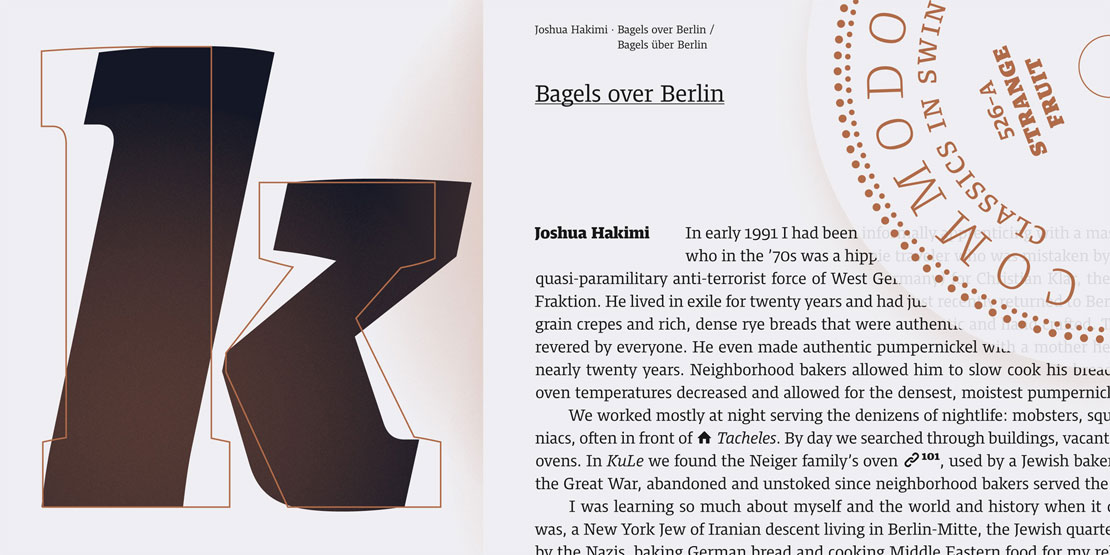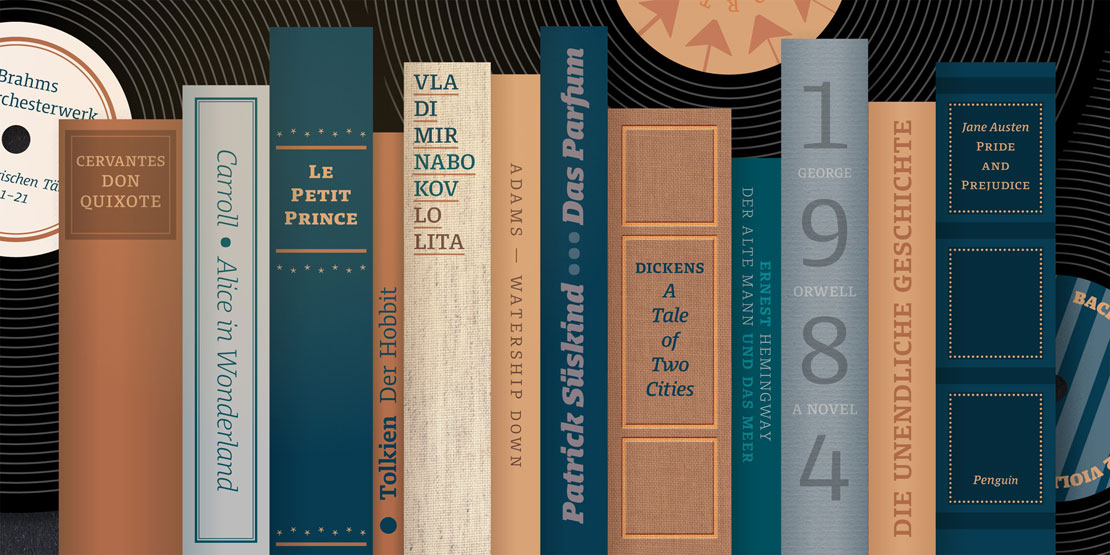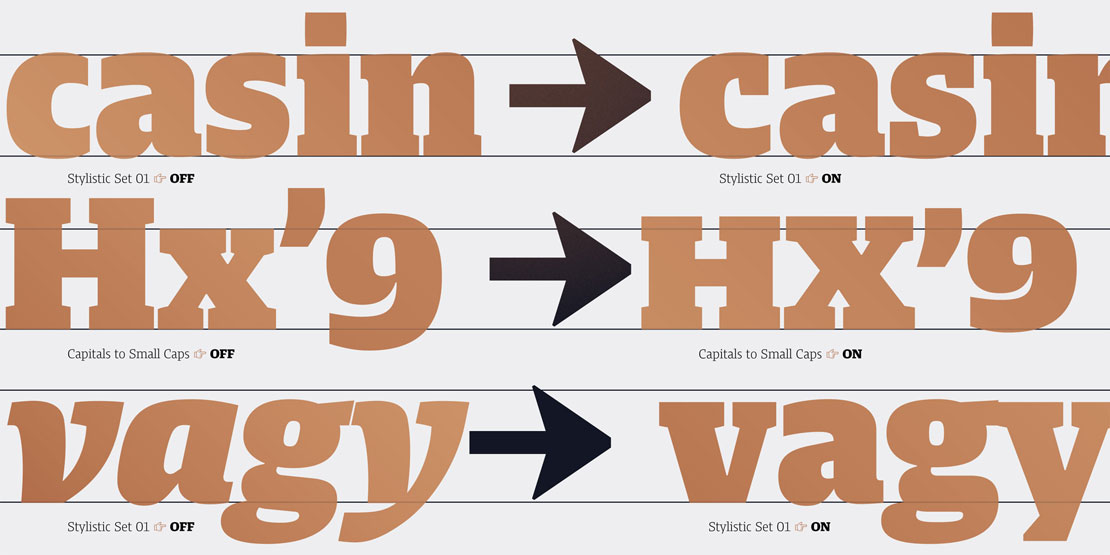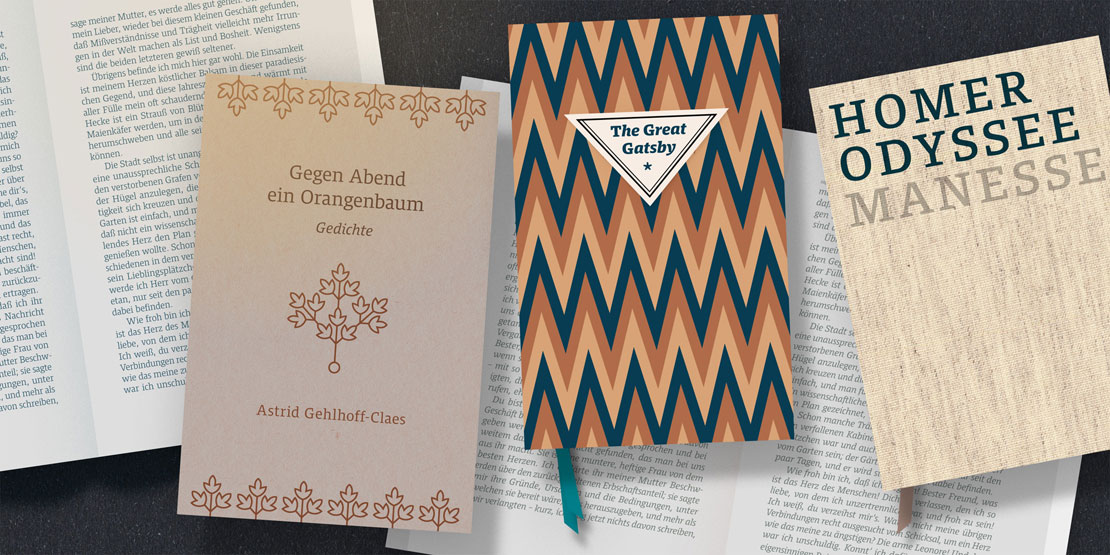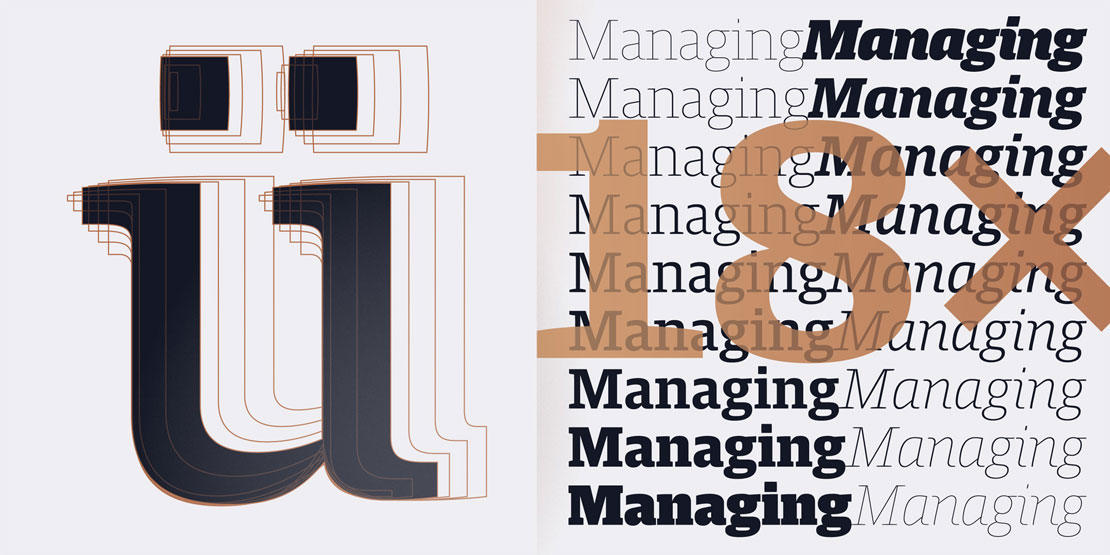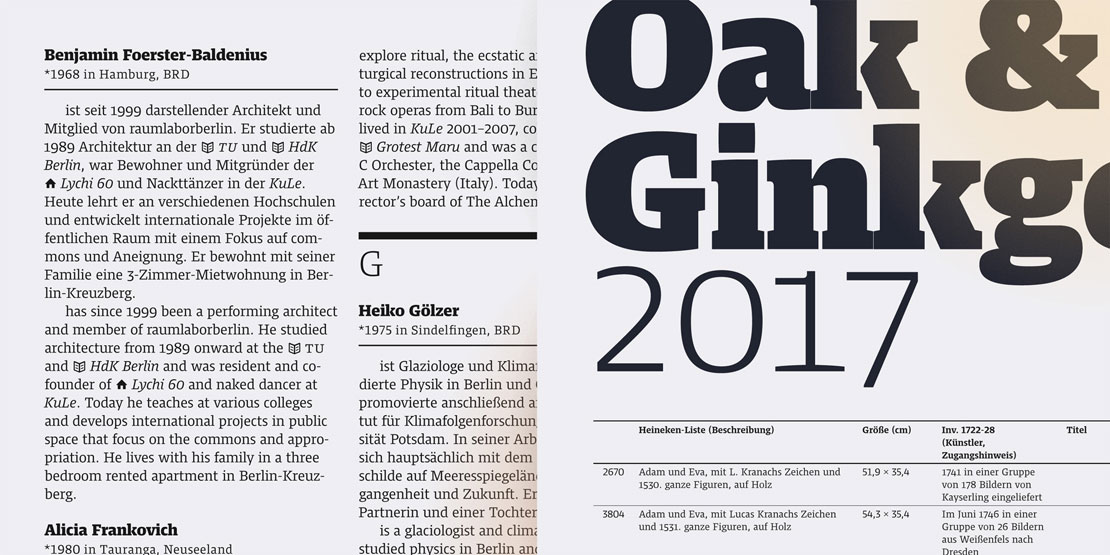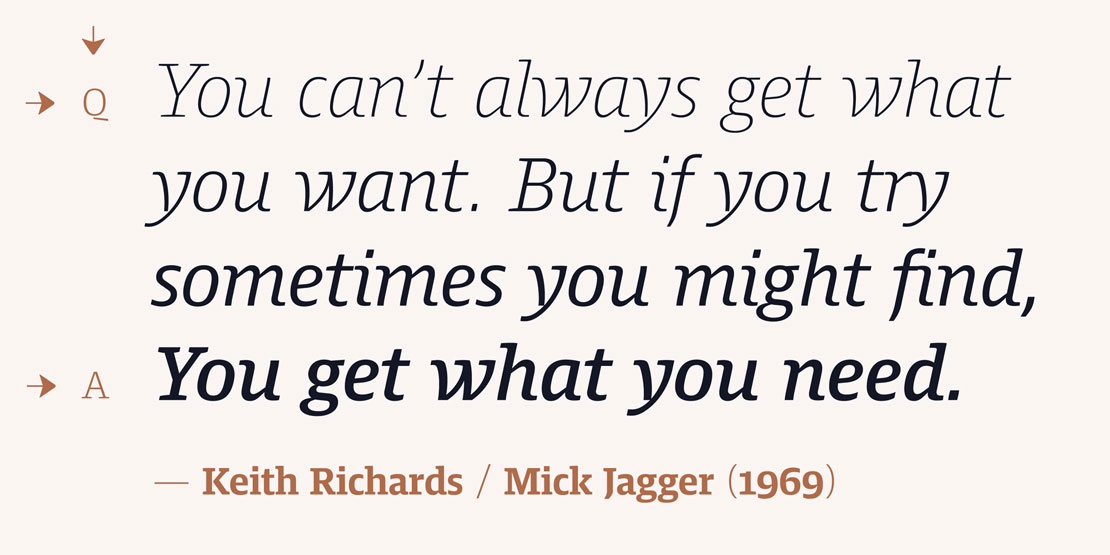
»Harrison Serif Pro« von den TypeMates
Die TypeMates aus Hamburg haben eine neue Schrift veröffentlicht. »Harrison Serif Pro« ist eine zeitgemäße Slab Serif im Spannungsfeld von kompetent bis leger.
Die Harrison Serif Pro von Jakob Runge und Lisa Fischbach ist eine robuste Slab Serif mit dezentem Strichstärkenkontrast, die Rationalität mit einem freundlichen Ton kombinieren soll. Die leicht gebogenen und teils stark betonten Serifen zeigen die sanfte Seite der Harrison Serif die im Kontrast zur gradlinigen Struktur der fast schon eckigen Innenformen, den offenen Punzen und der starken Betonung der Horizontalen steht.
Harrison wurde für längeren Text am Bildschirm und für UI Anwendungen gestaltet. Die ausgearbeiteten Details der Schrift sollen laut den Kreativen vor allem in hochauflösenden Medien und im gedruckten Umfeld zur Geltung kommen.
Harrison Serif bietet ein breites Spektrum an Gewichten – von hauchfeiner Haarlinie bis zur dunkelschwarzen Ultra sowie kursive Schnitte. Durch einen Mix aus echter Kursiven und schlicht geneigtem Winkel verbinden sie handschriftlich-verspielte, expressive Formen mit der Nüchternheit einer Oblique.
Die Schrift deckt einen breiten Lateinischen Sprachausbau ab und hat zudem noch einige hilfreiche Symbole in petto sowie nützliche OpenType-Funktionen.